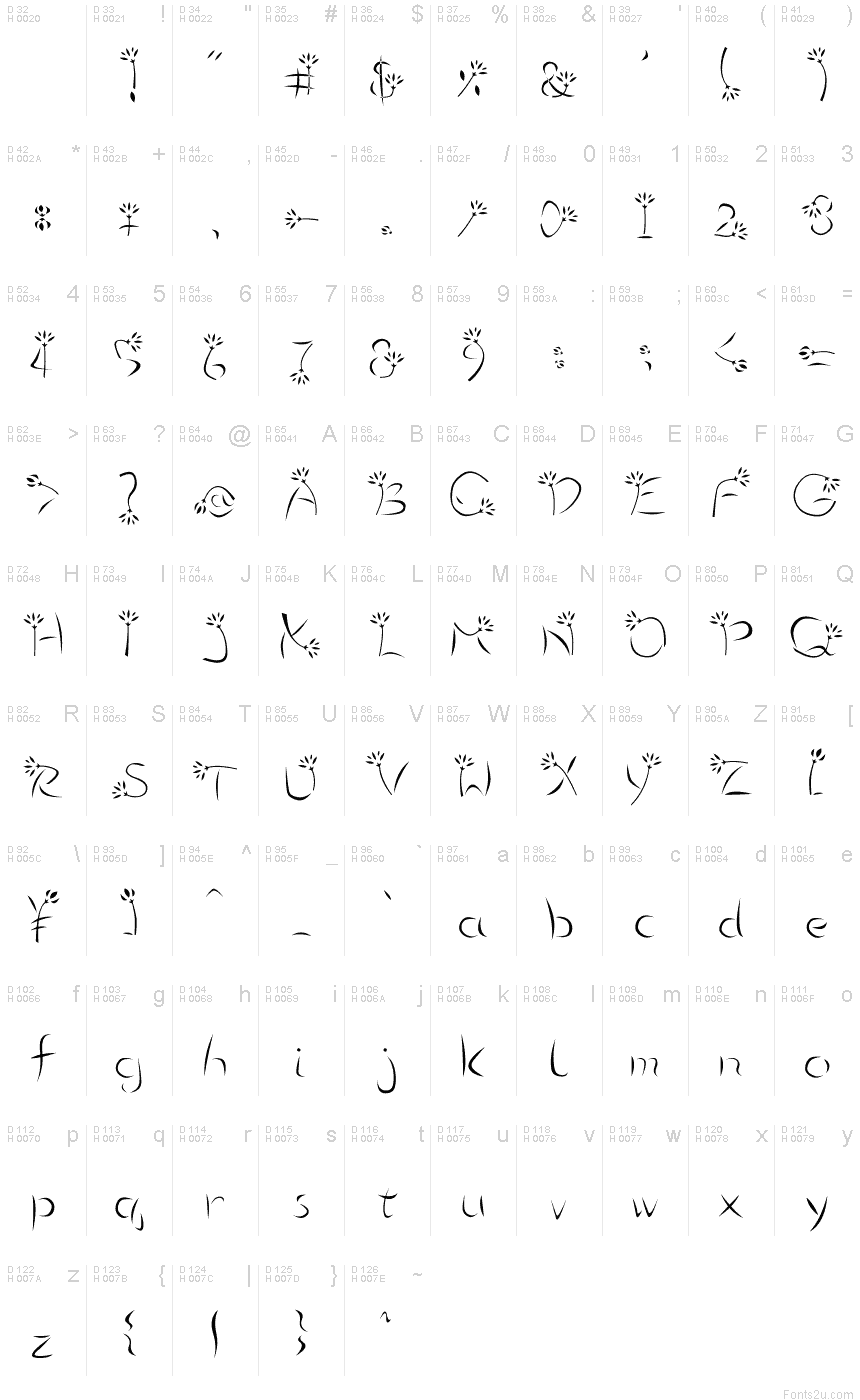
Flower3 di Rika Kawamoto è un carattere decorativo display gratuito che trasforma l'eleganza della grafia a mano in qualcosa di leggermente più selvaggio. Le sue lettere si intrecciano come rampicanti disegnati a inchiostro, con terminali appuntiti a forma di petalo e tratti ampi che risultano al contempo leggeri e studiati. Il ritmo è fluido e organico, tanto che le parole sembrano crescere sulla pagina anziché limitarsi a occupare spazio.
Usando Flower3, titoli e frasi brevi acquisiscono immediatamente un sapore poetico e ricercato, ideale per il branding di spa o saloni, packaging di prodotti di bellezza, titoli per matrimoni, copertine di libri di poesie, etichette di prodotti artigianali e post sognanti sui social media. Questo font gratuito dà il meglio di sé nei grandi formati, dove le sue curve originali possono respirare; abbinalo a un carattere sans serif pulito e leggero per il testo principale, così da mantenere il layout fresco ed equilibrato.